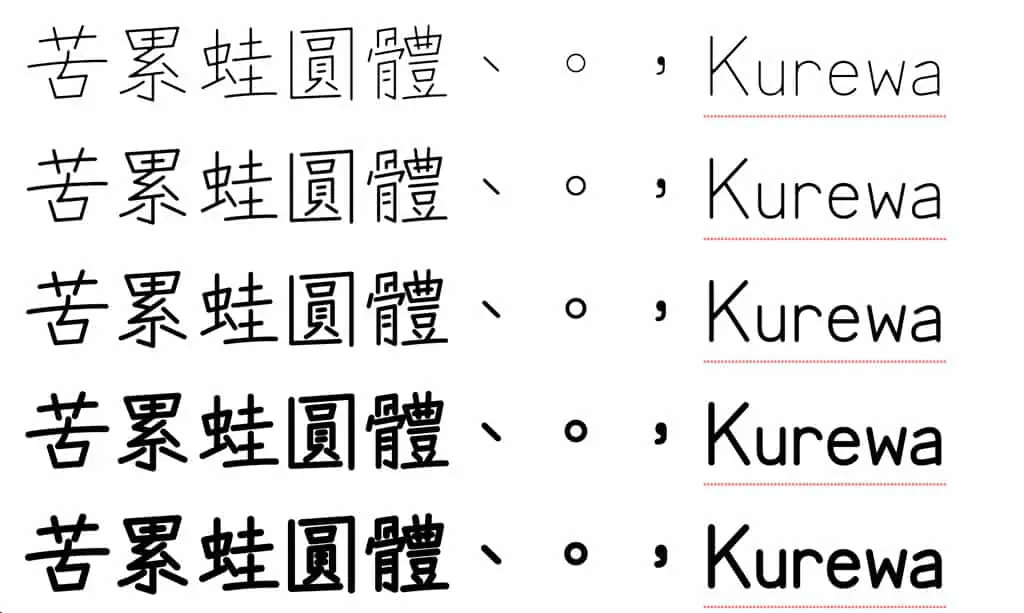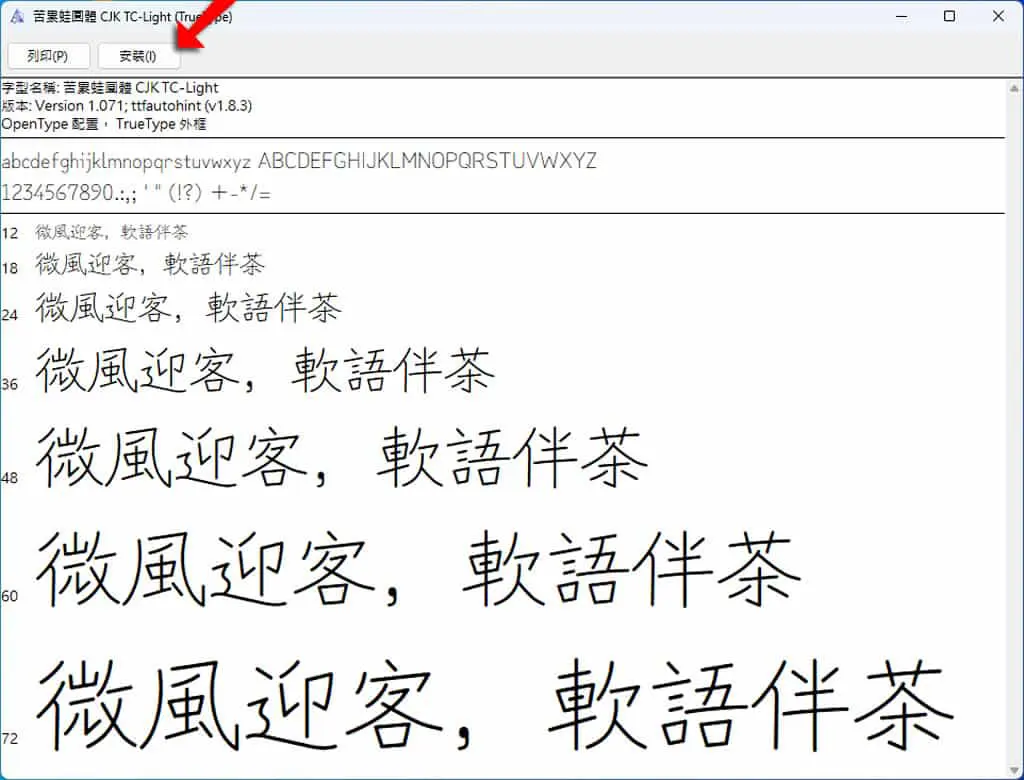
苦累蛙圓體 Kurewa Gothic:原子筆手寫風格中文字體,五種字重免費可商用
「苦累蛙圓體」是一個源於日文「紅道字體」的補字字型。紅道字體是一種具有手寫風格的日文字體,設計上省略了類似畫筆的元素,只保留字母的骨架,營造出原子筆手寫字母的印象。根據作者的說明,苦累蛙圓體與原作的主要差異在於調整了部件寫法,不僅補足繁體中文常用字的缺字,還增加了 Light、DemiLight、Regular、SemiBold 及 Bold 共五個字重。此外,它還將針對日本設計的全形標點符號調整為台灣常見的置中用法,並增加了臺灣閩南語和客語的部分中文字。「苦累蛙圓體」採用 SIL Open Font License 1.1 授權,允許免費商用並可自由優化與改作。
「苦累蛙圓體」雖源自日文紅道字體,但針對繁體中文使用者進行了重新設計。不僅提供多種字重選擇,還調整標點符號位置,增加臺灣閩南語和客語的部分中文字,使其更符合台灣常見用法。這款字型完全免費且可商用,是類手寫字型的理想選擇。